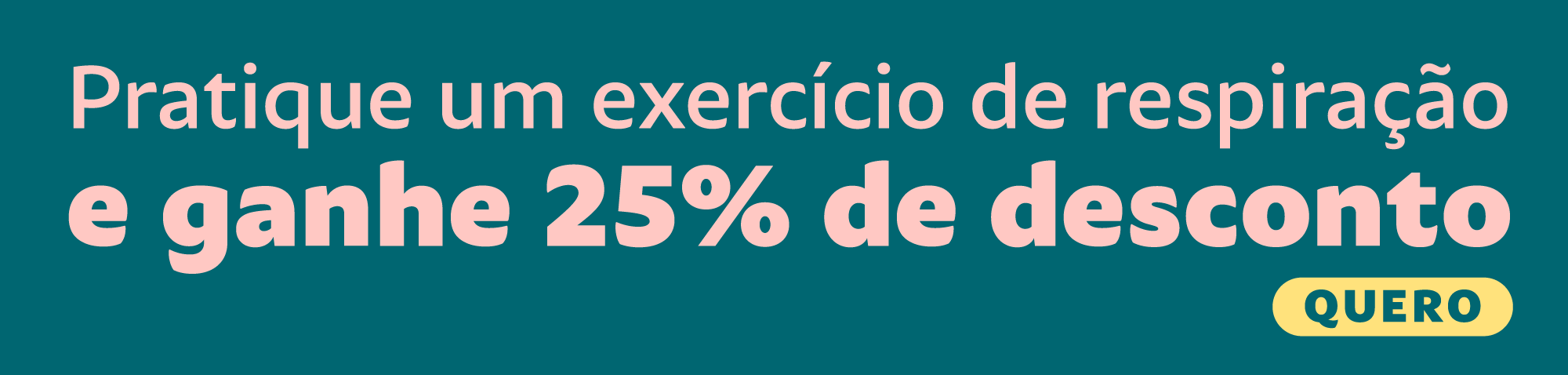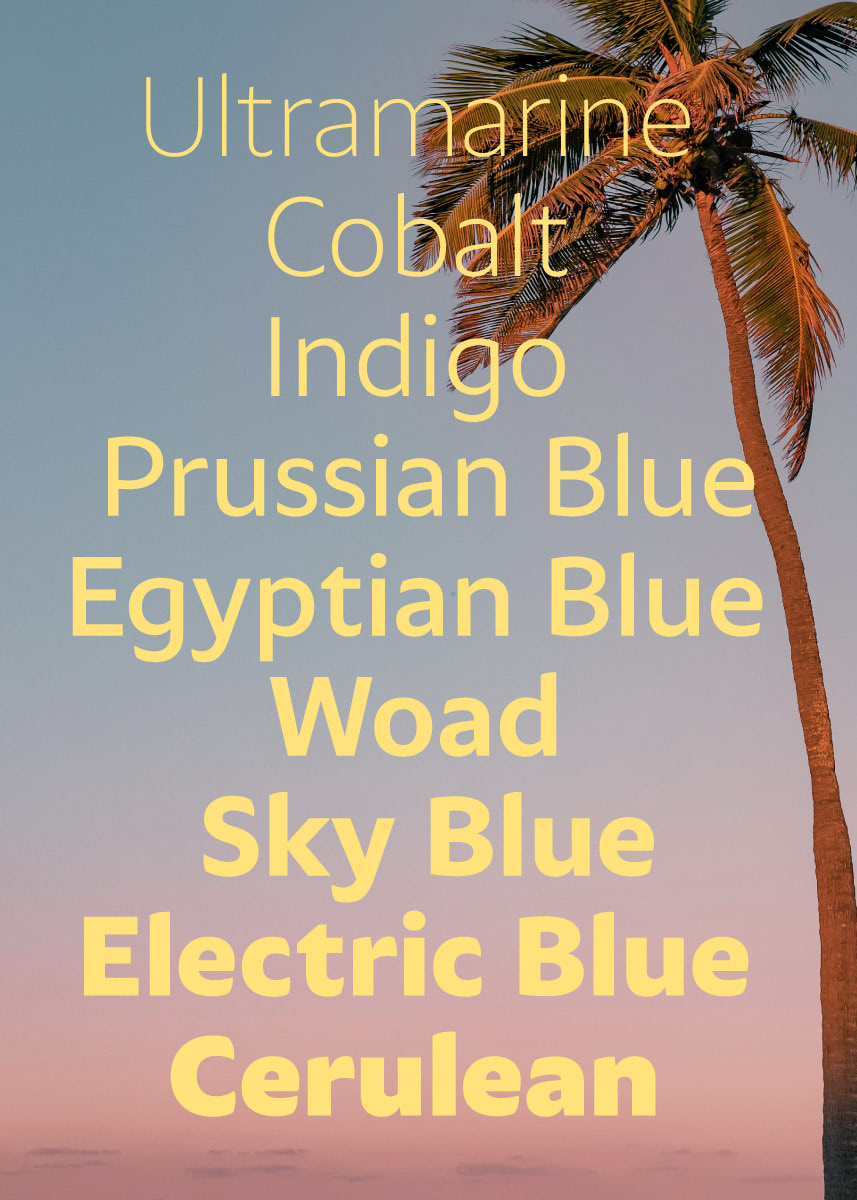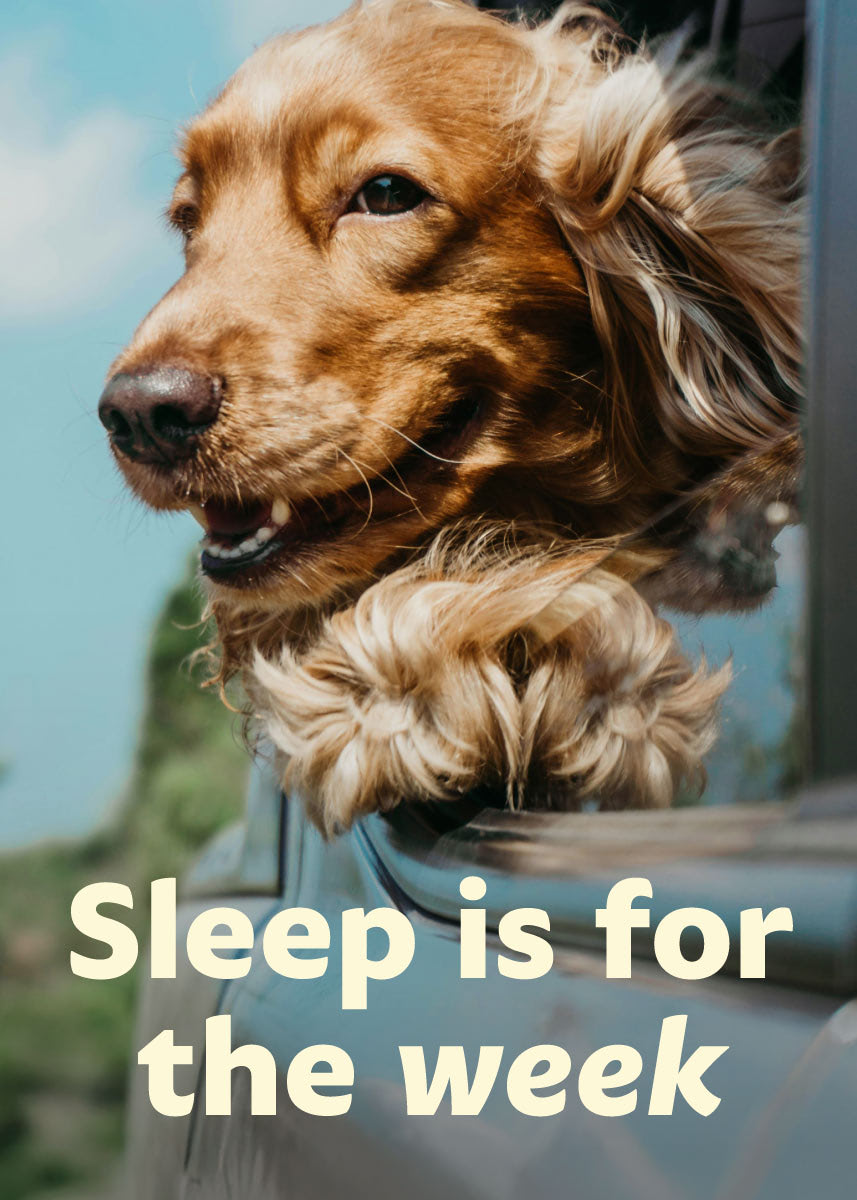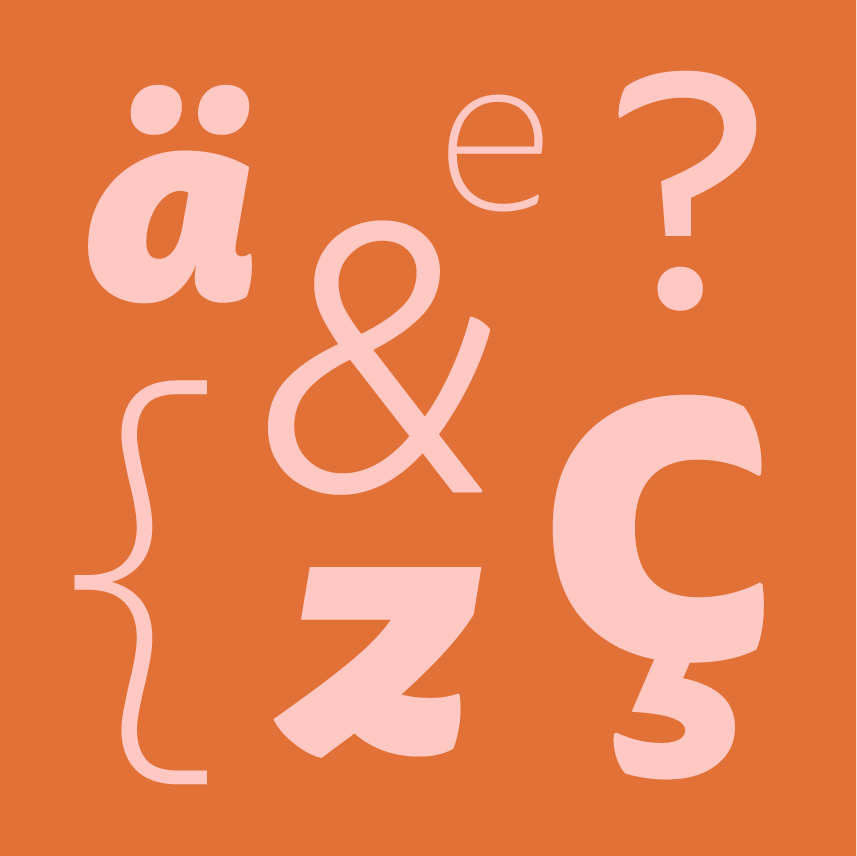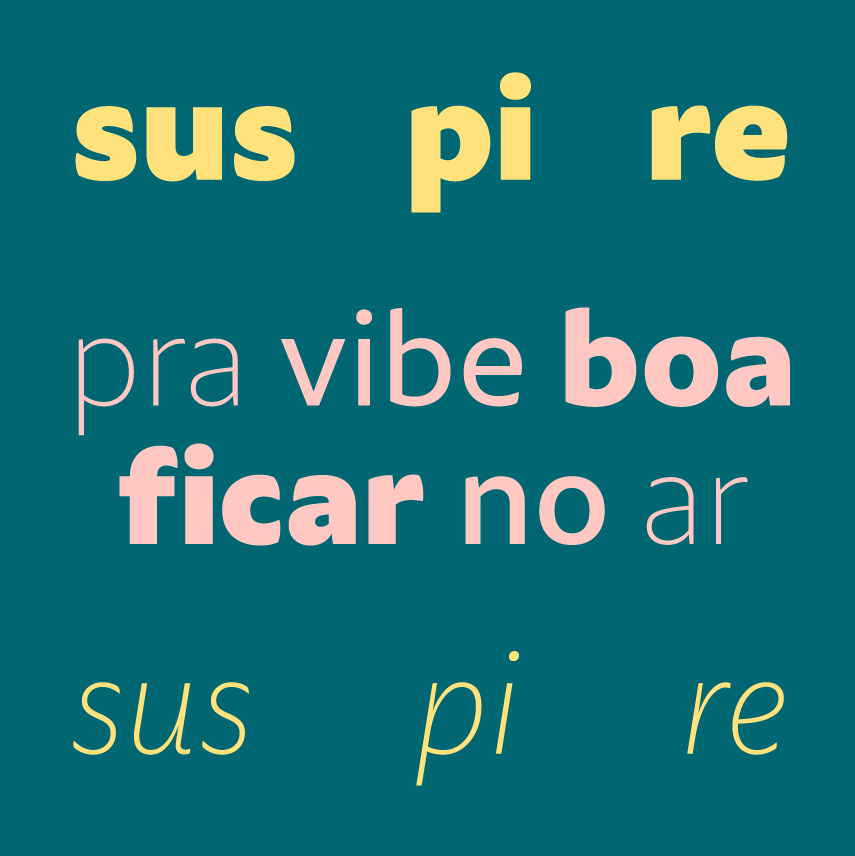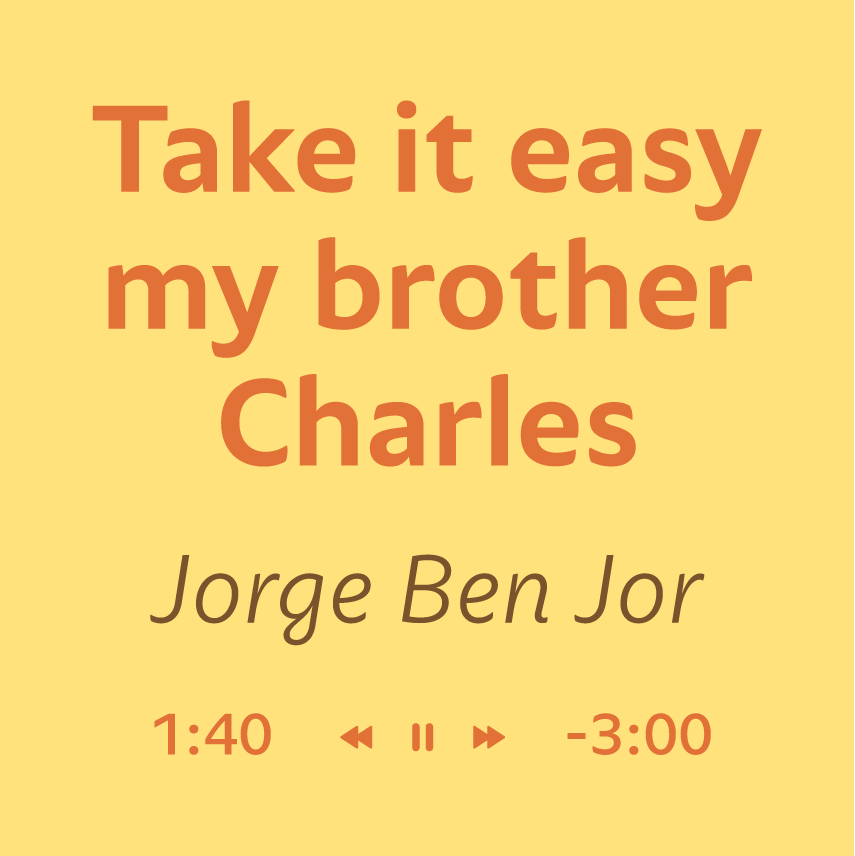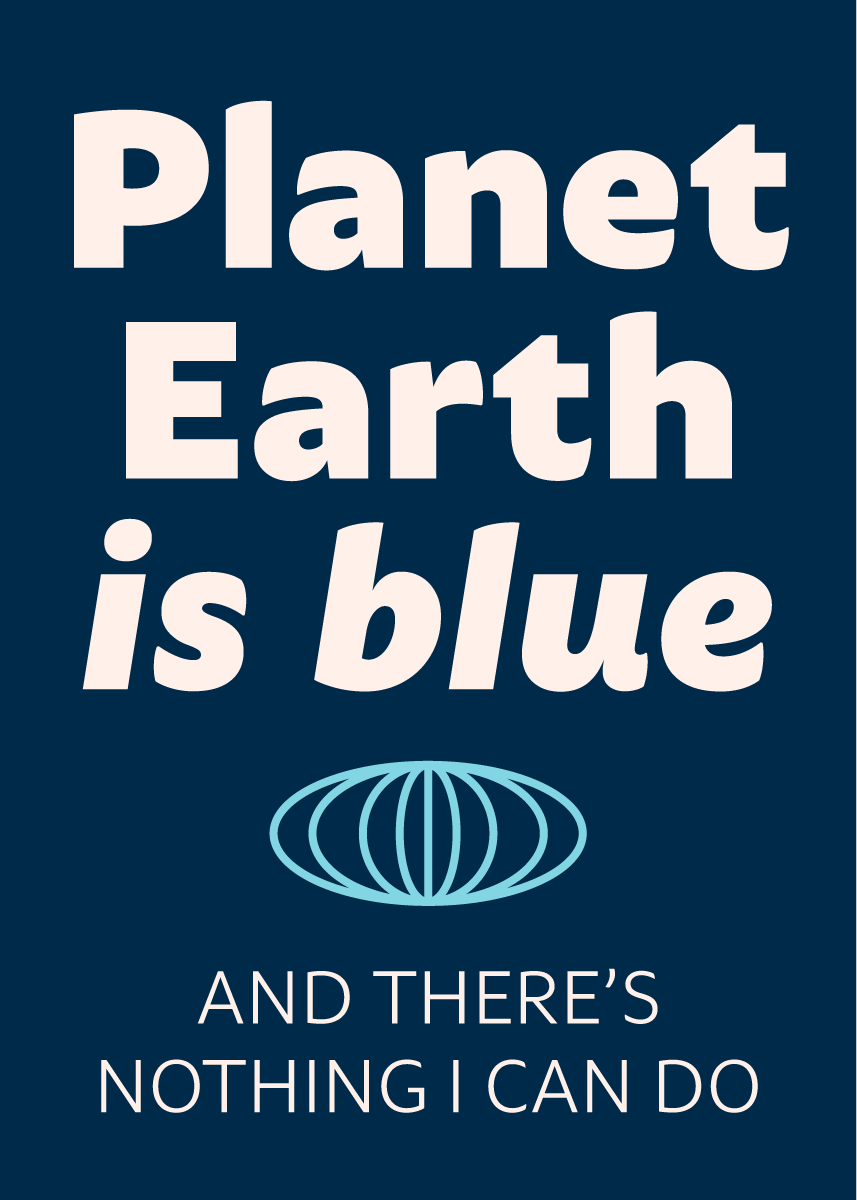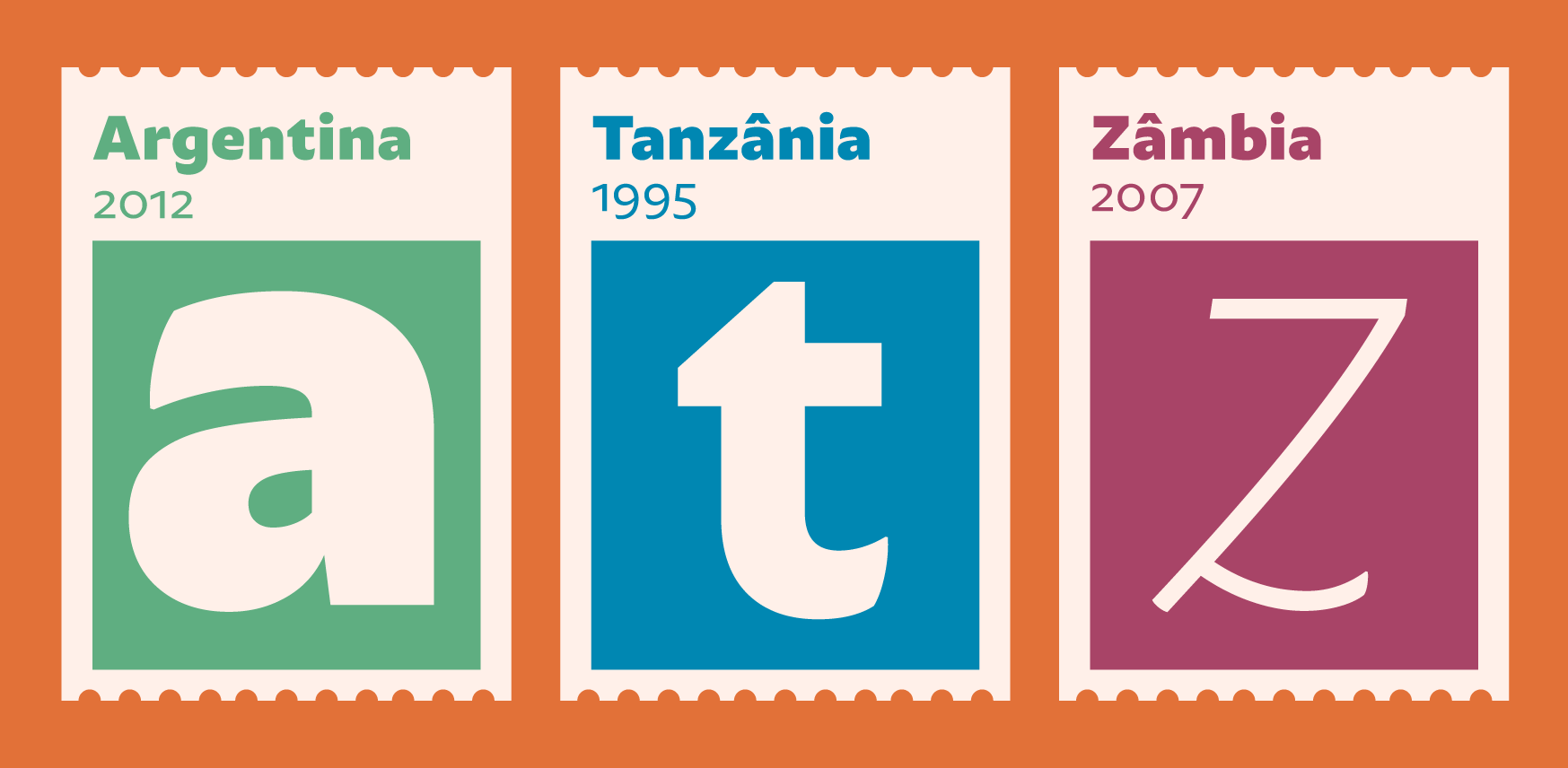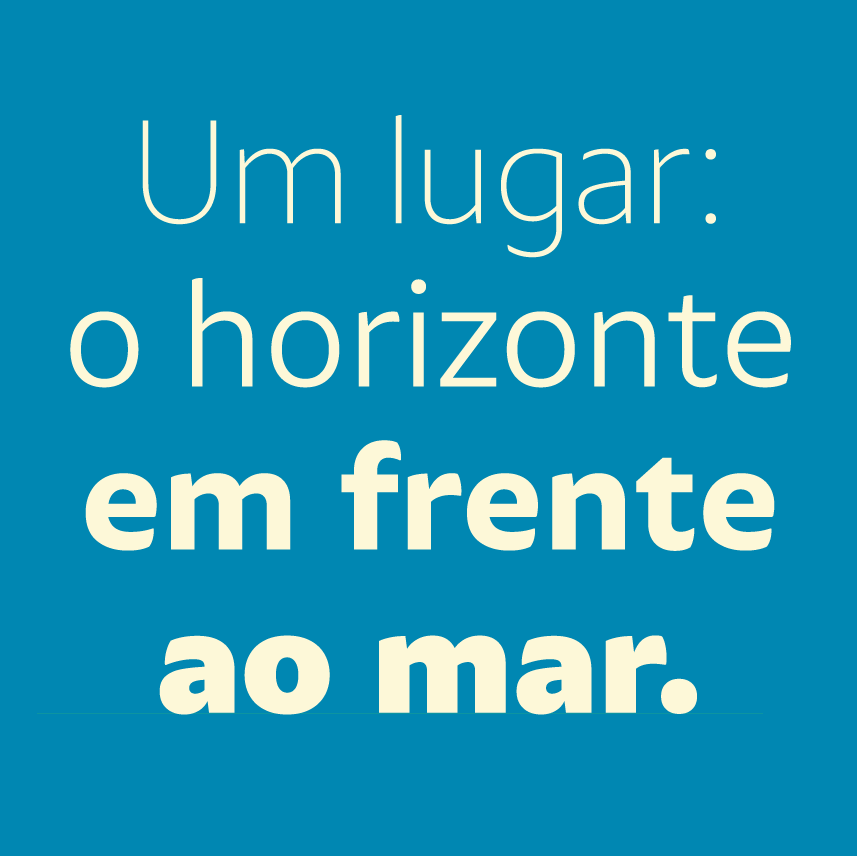
Suspire
A typeface that carries a gentle reminder
We can take it easier
Like a river, let it flow
Gente boa, vibe boa
Made to dream, converse, uncomplicate
If Suspire was a place
The horizon in front of the sea
É como brisa leve que chega de mansinho
It’s about the journey
Sus pi re. Uma tipografia que leva um lembrete gentil: a gente pode pegar mais leve.
A suspire é do tipo que tem o balanço que aproxima: o estilo humanista, da base sem serifas. Pra trazer conforto mesmo em letras pequenas. Os terminais calorosos, dos acenos caligráficos. Pra conversar com a leveza da mão que escreve em um encaixe bonito de se ver.
Algumas letras tem variações, pra mostrar a personalidade de quem chama todo mundo pra conversa. A Suspire não grita, mas se você parar pra ver, tem presença. Seus detalhes curvos dão o ar da graça à medida que o peso e o tamanho sobem. É como brisa leve que chega de mansinho, mas sem passar despercebida.
A Suspire é gente como a gente. Feita pra sonhar, conversar, descomplicar. É pra ser como o ser humano é: criativo, empático, real. Porque ser humano, na verdade, é parar pra suspirar.
Ah. Aquele suspiro feliz que a gente dá quando encontra a type que é a vibe do projeto. Uma type que lembra como é bom se soltar. Suspire. Pra vibe boa ficar no ar.